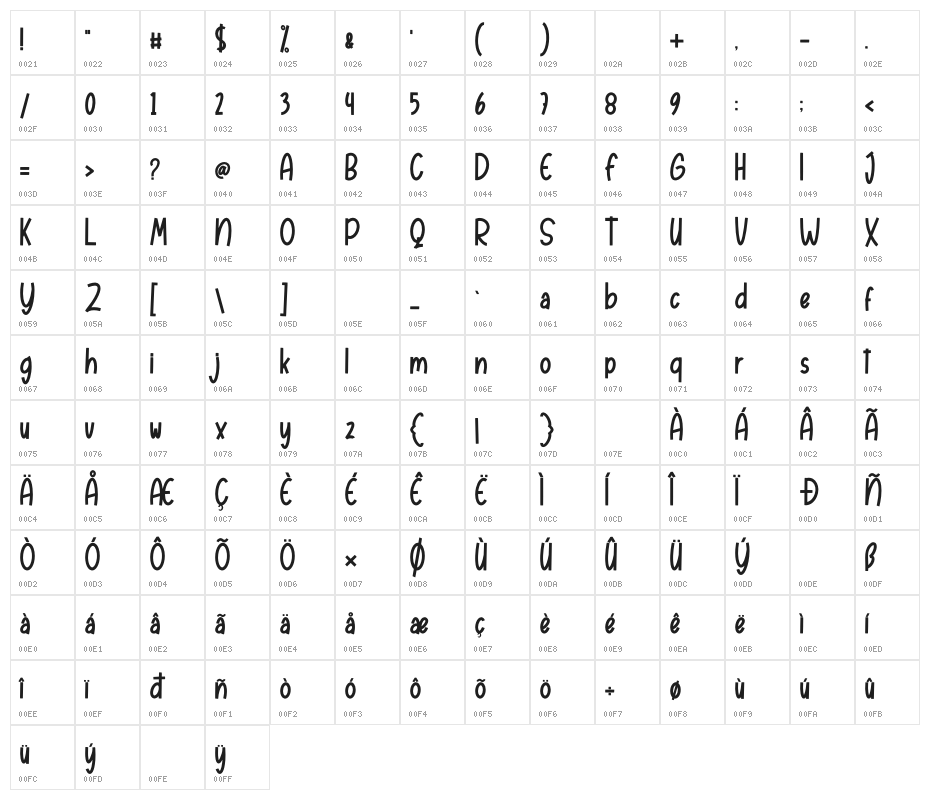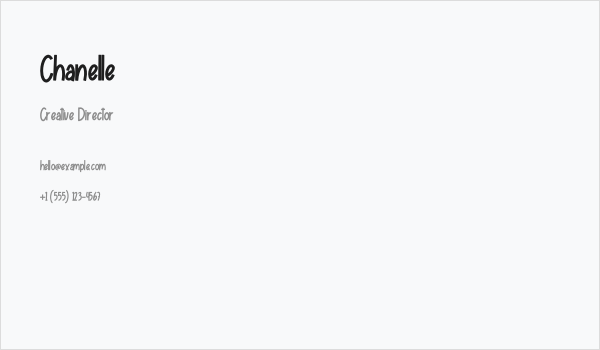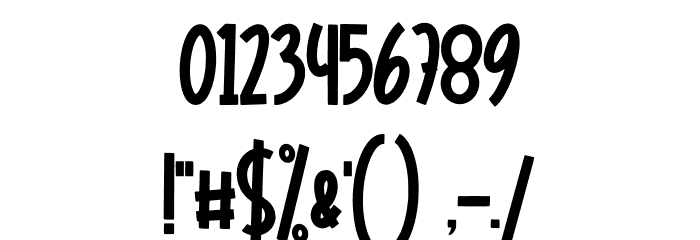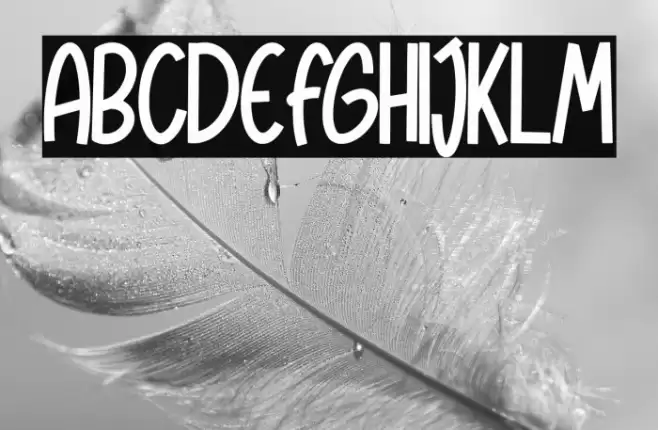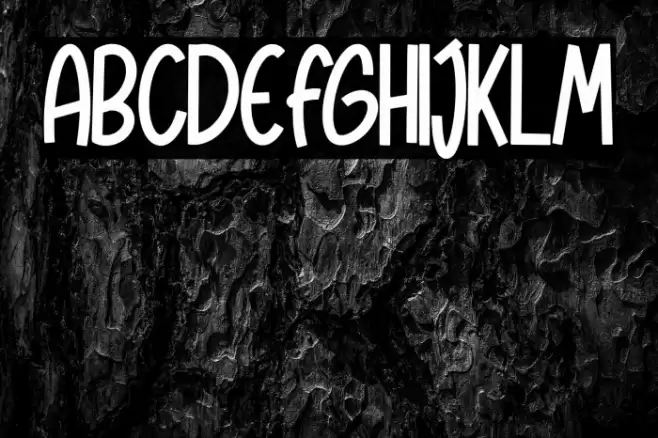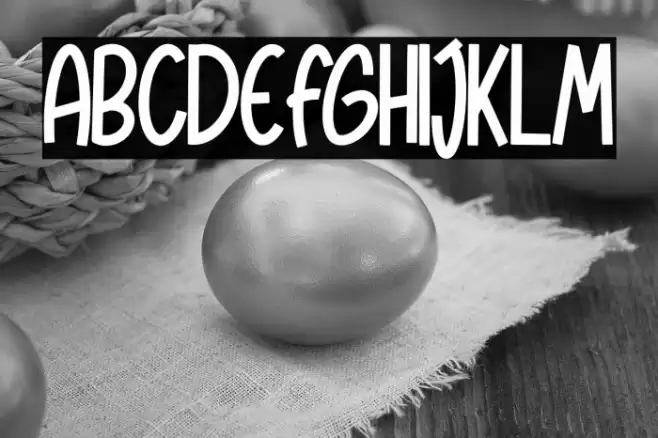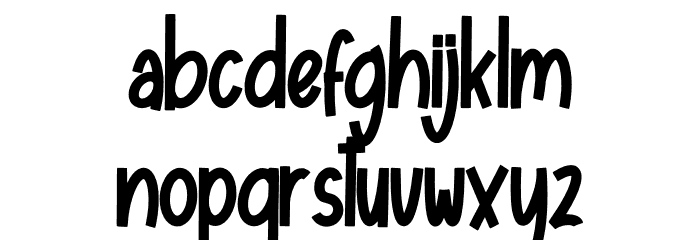
Chanelle Font
| النمط العام | Playful |
| حالة الاستخدام | Logos, Headlines, Creative projects |
| مشاريع مقترحة | Ideal for greeting cards, children's books, playful branding, and creative posters. |